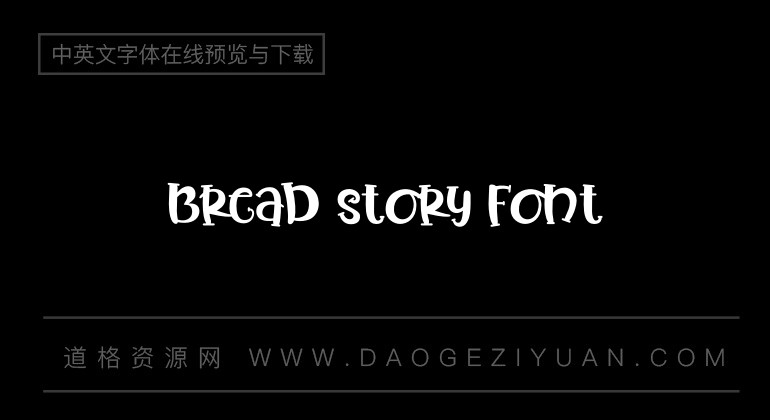
Bread Story Font
Bread Story Font 是一款由设计师 Rizal Khurasan 制作的免费字体。它的风格是装饰性的手写风格,非常适合用于餐厅菜单、面包店标志、食品包装等设计项目。这种字体有许多可爱的曲线和线条,使得文字看起来非常有趣和吸引人。Bread Story Font 包含大写字母、小写字母、数字和标点符号,它可以在商业和个人项目中免费使用。如果你正在寻找一款有趣而装饰性的字体来增强你的设计项目,Bread Story Font 是一个不错的选择。
Bread Story Font是一款非常不错的手写艺术字体,具有很好的视觉感,适合于文化类的宣传设计、商业类品牌的广告和产品包装设计以及个性化文字排版等较多场景。